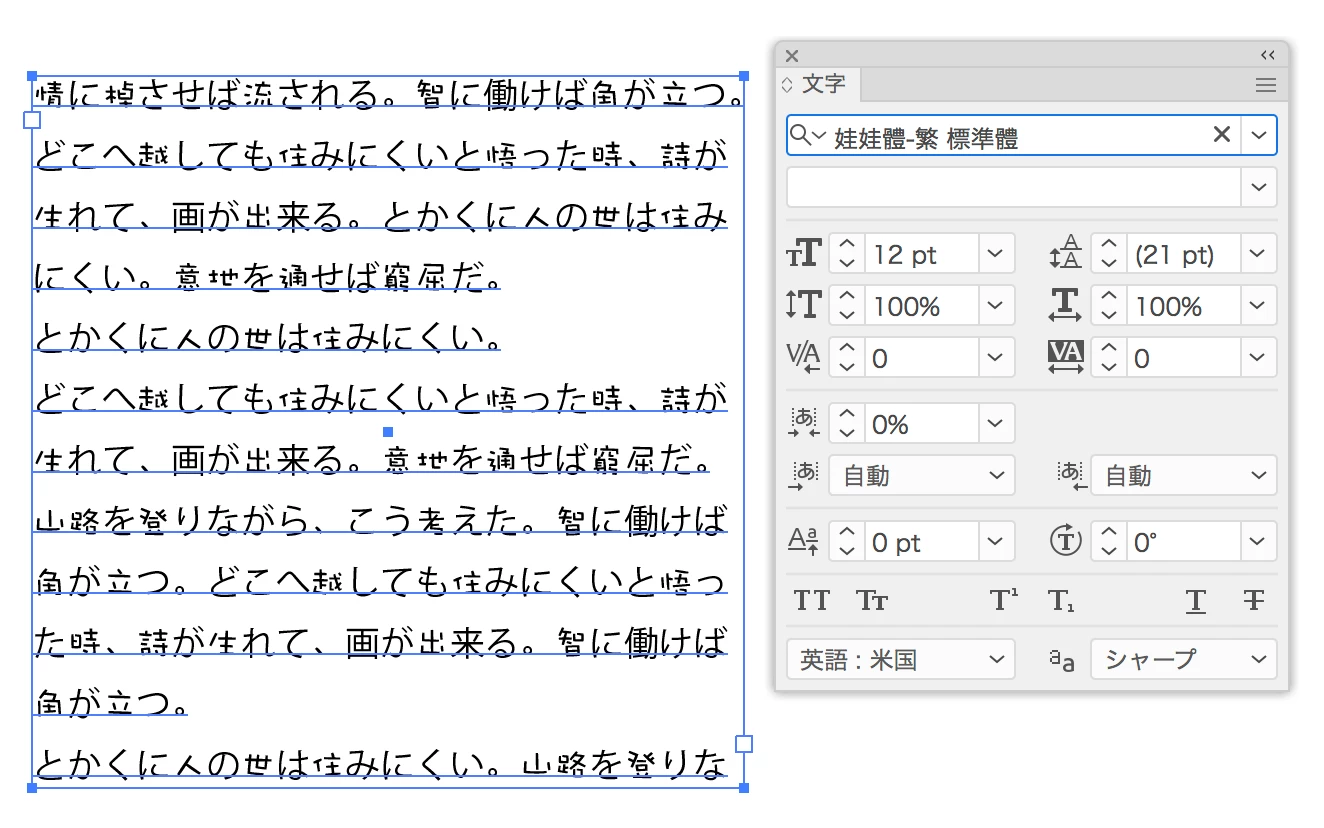
娃娃體-繁 標準體というフォントについて
これですね!
ちなみに繁体字だけでなく簡体字もあります。可愛らしいデザインなのであちらの印刷物や看板などでもちょいちょい見かけます。
AdobeIllustratorに搭載のフォントではなく、macOSに搭載のフォントで、最新版のCatalinaにも入ってます。
実際に利用しているIllustrator上でそのフォントが文字パネル等で出てくるのでしょうか。
また、出てくるとした場合は、Illustratorの環境設定-テキストで、「フォント名を英語表記」にチェックを入れてフォント名を確認することになります。
もし現時点でメニュー等に出てきてないものであれば、その情報をどこから得たのか、という点になってきます。
ちなみにフォント名でGoogle検索すると一応ヒットしますが、最初にヒットするものを見る限り、ダイナコムウェアのクラフト遊に近いものが出てきます。
英語表記にしたら、Wawati SC Regular と出てきました!
mac OS Sierraでフォントブックからダウンロードできるものとのことです。
25年以上Illustratorを使っていますが、日本語版でそんなフォントが付属したことはないはずです。
中国語書体としてもないですか?
パッケージに付属していたものとしては、次のページにあるものですべてです(これより古いバージョンには、これにない欧文フォントがありますが、その時代には中国語フォントは一切含まれていません)。